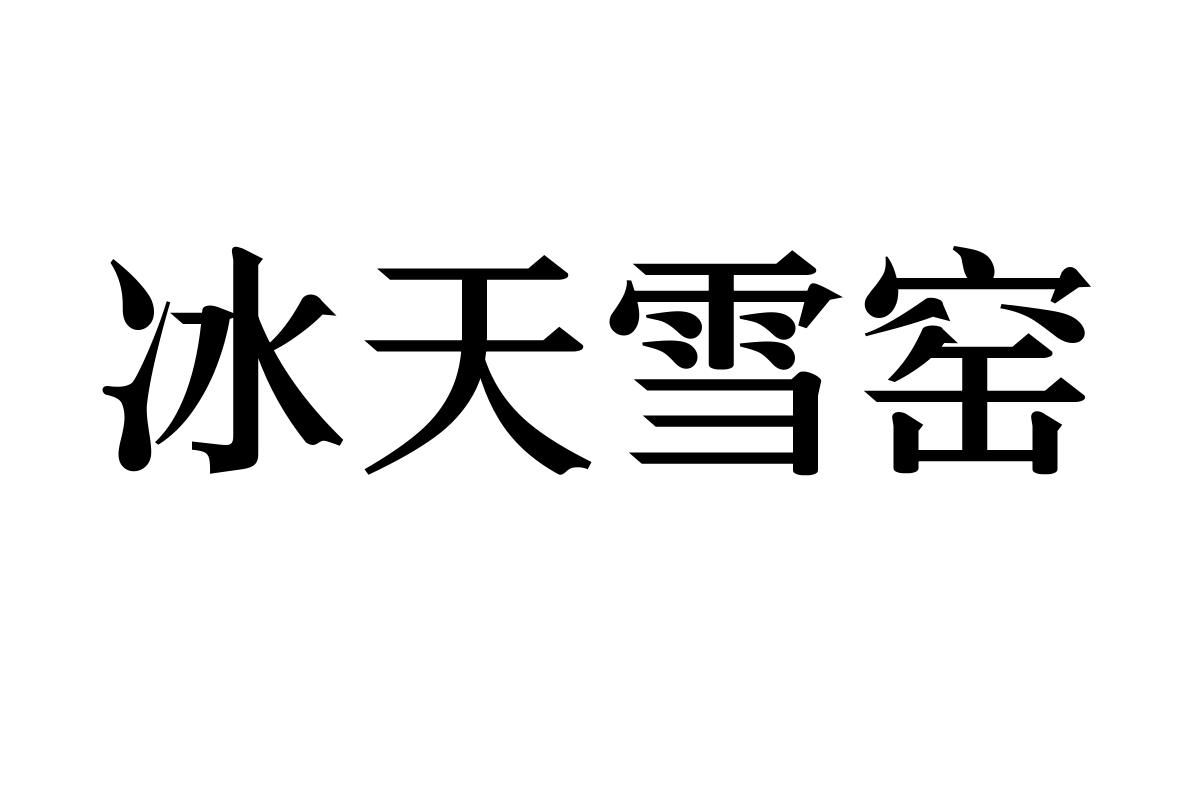
三极萧宋简体粗字体是一种常见的中文字体,主要用于排版和印刷。它具有以下特点:
1. 字形:三极萧宋简体粗字体的字形简洁大方,线条流畅自然,给人一种优雅的感觉。
2. 结构:这种字体的结构紧凑,笔画粗细适中,既不会过于繁琐也不会过于简单,适合用于各种类型的文字排版。
3. 易读性:由于字形简洁,笔画粗细适中,因此这种字体的易读性较好,方便读者阅读。
4. 适用范围:三极萧宋简体粗字体适用于各种类型的文字排版,如报纸、杂志、书籍、广告等。
总之,三极萧宋简体粗字体是一种实用且美观的中文字体,广泛应用于各种文字排版中。